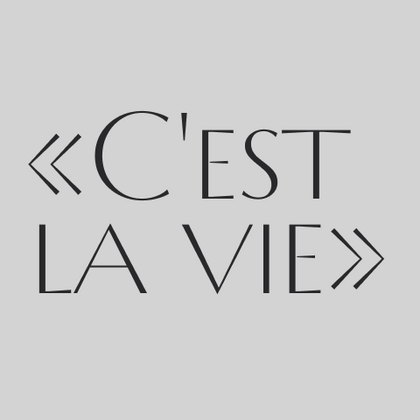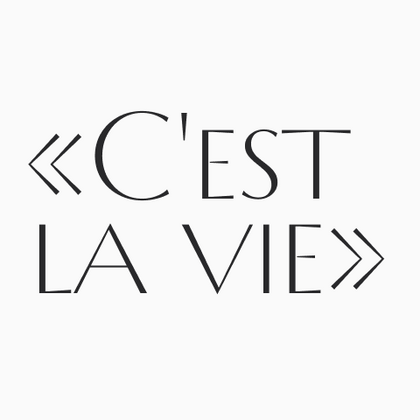
Шрифты для цитат
Созданные для выразительного оформления значимых высказываний шрифты для цитат отличаются изящными пропорциями, умеренным контрастом штрихов и благородной эстетикой, подчеркивающей важность текста. TypeType представляет как классические каллиграфические варианты с деликатными росчерками, так и современные интерпретации — все они идеально передают эмоциональную нагрузку цитат, сохраняя при этом безупречную читаемость.
TT Supermolot Neue — технологичный модульный гротеск с футуристическим настроением и мощным функционалом. Яркость его характера сочетается с универсальностью применения.
TT Rationalist — функциональный и оригинальный брусковый шрифт с актуальным рисунком. Он универсален и подходит как для заголовков, так и для массивов текста.
TT Turns — геометрический гротеск с акцентными круглыми знаками и выразительными нависающими элементами. Это универсальный шрифт, который лаконично выглядит и отлично читается в маленьком размере, при этом в крупных кеглях становится акцидентным и проявляет свой характер на максимум. Он энергичный, сильный и динамичный — особенно отчётливо это проявляется в наклонных начертаниях.
TT Regins — шотландская новостильная антиква с королевским характером. Яркий контраст и острые треугольные засечки придают этому шрифту строгий и властный нрав.
TT Moons — узкая и контрастная антиква. Данное шрифтовое семейство очень элегантно работает в классических темах дизайна. TT Moons по стилистике относится к глиптальным новостильным шрифтам. Идеальная сфера использования TT Moons — это верстка журналов, книг и газет.
TT Firs Neue — скандинавский гротеск, сочетающий выразительные графические элементы с универсальностью использования. Мы проанализировали каждый контур и графический элемент. Пересобрали шрифт заново, чтобы сохранить лучшее и исправить необходимое.
TT Disruptors — дуктальный рукописный шрифт, созданный с помощью маркера. Его рисунок уникален: потёртости, неравномерная толщина штрихов и удлинённые выносные элементы придают ему живую, динамичную текстуру и ощущение рукотворности. Характер этого шрифта своенравный и эмоциональный, но при этом тёплый и душевный.
TT Ramillas — стильная и современная антиква. Включает уникальные декоративные начертания и буквицы с цветочным орнаментом.
TT Gertika — геометрический гротеск с динамичным характером и танцующим ритмом. Идея шрифта зародилась из леттеринга на американском плакате второй половины 30-х годов.
TT Biersal — акцидентный гротеск со свободным, озорным и авантюрным характером. Отправной точкой для его создания послужил немецкий плакат начала 30-х годов. Мы хотели сохранить не только пропорции, но и ощущение небрежности, живости леттеринга из референса.
TT Cometus — современная брусковая антиква. Название гарнитуры отсылает к образу кометы — мощного увесистого тела с красивым хвостом, грациозно рассекающего космические просторы с огромной скоростью.
TT Carvist — современный экспериментальный гротеск со сверхузкими пропорциями. Название гарнитуры отсылает к резьбе по камню: характерные черты этого шрифта — геометричность и брутальность.
TT Espina — дисплейная антиква с выразительными засечками. При ее создании дизайнеры вдохновлялись исторической формой буквы «O», которая приобретала ромбовидную форму из-за качества печати. В каждую букву хочется всматриваться, так что заголовки, оформленные TT Espina, точно привлекут внимание.
Забудьте всё, что вы знали о TT Smalls, ведь мы перевыпустили шрифт! Оформляйте выразительные заголовки, применяйте в оформлении упаковок или выделяйте текст на сайте.
TT Marxiana является проектом по реконструкции набора дореволюционных шрифтов, которые использовались в изготовлении и печати журнала «Нива» 1887 года выпуска, а именно на его антикве и италике, гротеске и эльзевире.
TT Polls берет свое начало как современный модульный брусковый шрифт. При создании шрифтового семейства TT Polls мы держали в голове его использование в дизайне на спортивную тематику, но финальная версия TT Polls отлично подходит и для более казуального дизайна и сфер применения.
TT Berlinerins — это контрастная пара шрифтов, которая по сути является нашим трибьютом Берлину. Также, как и в самом городе переплетаются историчность и современность, так и в нашем шрифтовом семействе элегантный скрипт символизирует собой современный Берлин, а гротеск, выполненный в стиле плакатных wood-type шрифтов первой трети 20-го века, отвечает за историческую составляющую города.
Первоначально идея шрифтового семейства TT Milks заключалась в том, чтобы создать коллекцию шрифтов для использования в упаковке и брендинге молочной продукции.
TT Octas — шрифтовое семейство с узкими пропорциями, построенное по принципу октагональности, в данной гарнитуре все окружности представляют из себя восьмигранники. Благодаря небольшим засечкам Октас приобретает насыщенный и старинный характер.
TT Prosto Sans является шрифтовой гарнитурой на любой жизненный случай. Благодаря современным открытым гротескным формам, вы можете использовать гарнитуру почти для любой задачи.